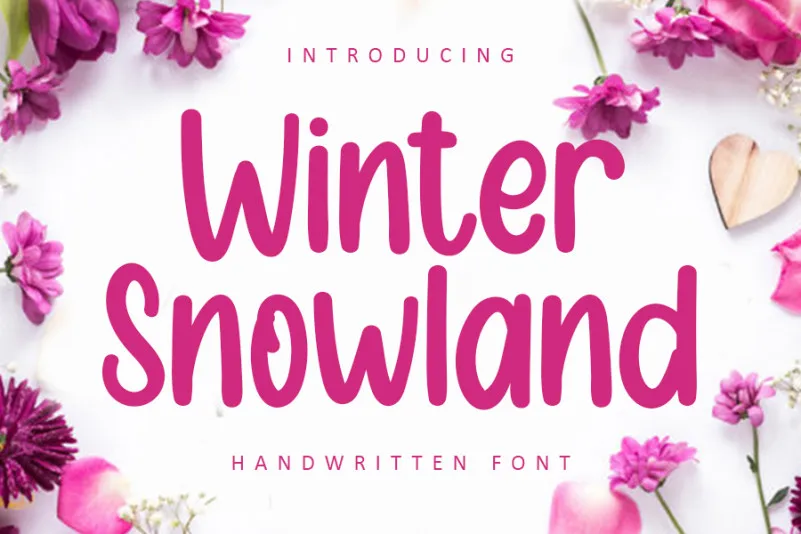
Winter Snowland Display Font – Download Grátis
A Winter Snowland Display Font é uma elegante tipografia escrita à mão que transmite tranquilidade e simplicidade. Este tipo impecável pode ser aplicado a diversos projetos de design, seja para criar um toque pessoal em cartões de aniversário ou adicionar um apelo natural aos posters decorativos. Perfeita tanto para designers digitais quanto para amantes do papel que buscam um toque autêntico nos seus trabalhos manuais. Feito especialmente pelo designer freshtypeink, esta fonte escrita à mão simples e equilibrada é uma ótima escolha para todos os momentos em que você deseja dar vida a um projeto com personalidade e beleza. Suavemente convidativa, essa fonte de display é perfeita para destacar visivelmente seus trabalhos de design. Sua facilidade de uso torna-a acessível para designers digitais, enquanto sua natureza rica em detalhes e harmoniosa em proporções faz dela uma ótima escolha para artistas que desejam incorporar um toque autêntico aos seus designs manuais.
Designer: freshtypeink